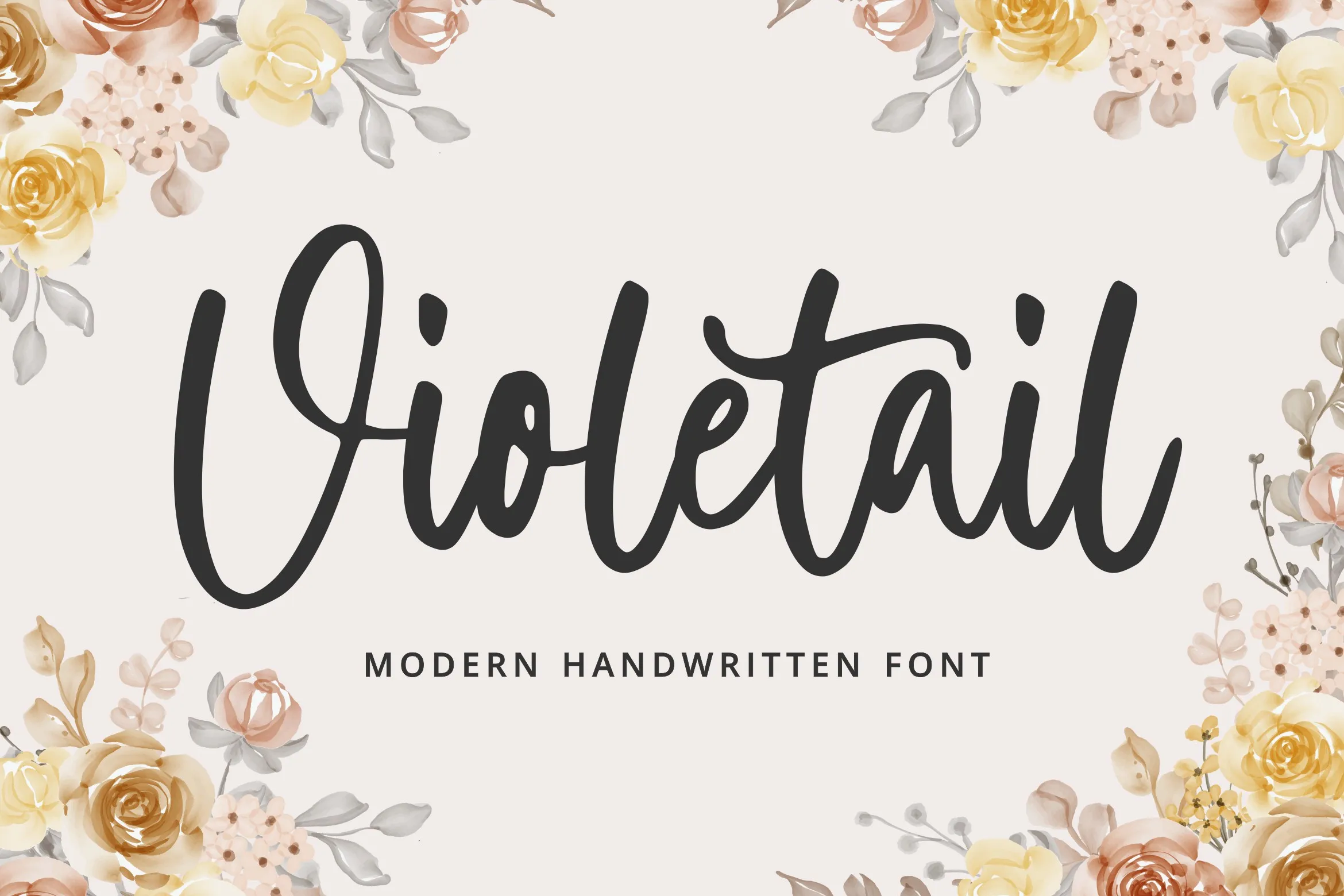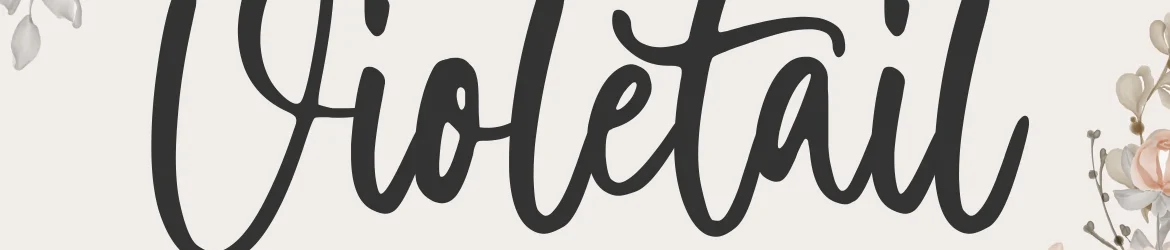
Violetail Font – Download Grátis
A Violetail Font é uma elegante fonte escrita a mão que traz suaves e delicadas curvas para suas criações. Esta originalidade chama a atenção tanto para ideias crafty como para títulos, cartão de visita ou papelão personalizado. Com seus detalhes finos e seu aspecto charmoso, esta fonte é perfeita para qualquer projeto que você possa estar planejando, desde o título da sua próxima campanha até o design do seu próximo livro. A Violetail Font é um ótimo complemento para designers a fim de dar ao seu trabalho um toque pessoal e sofisticado.